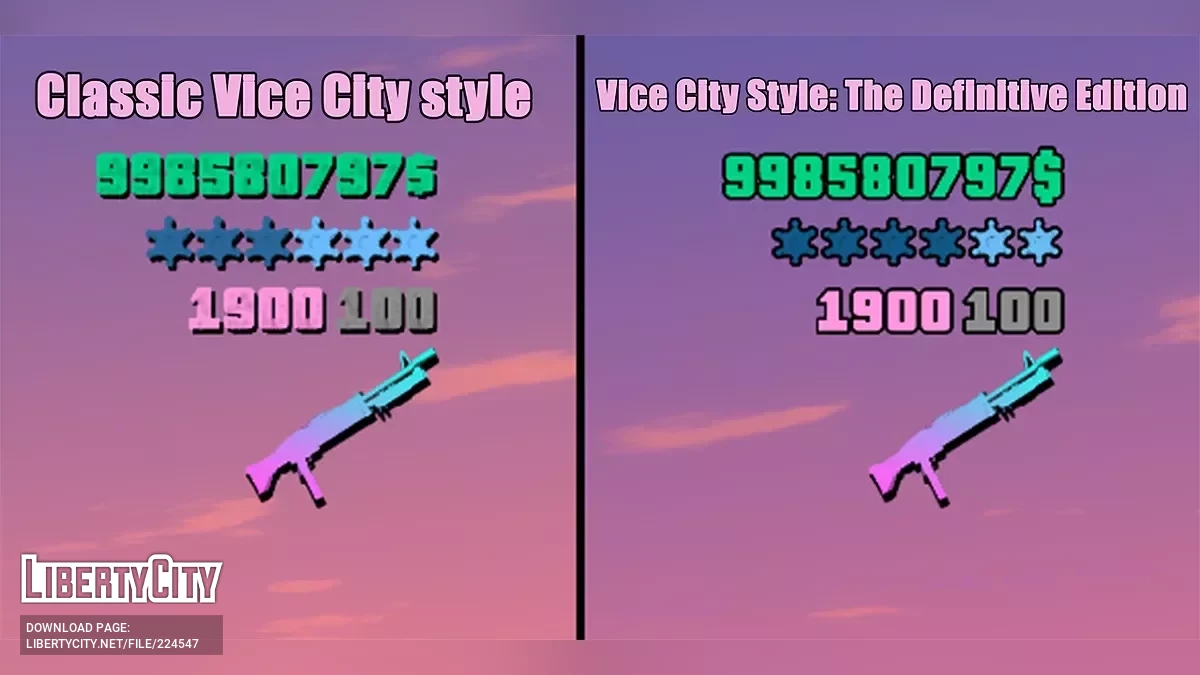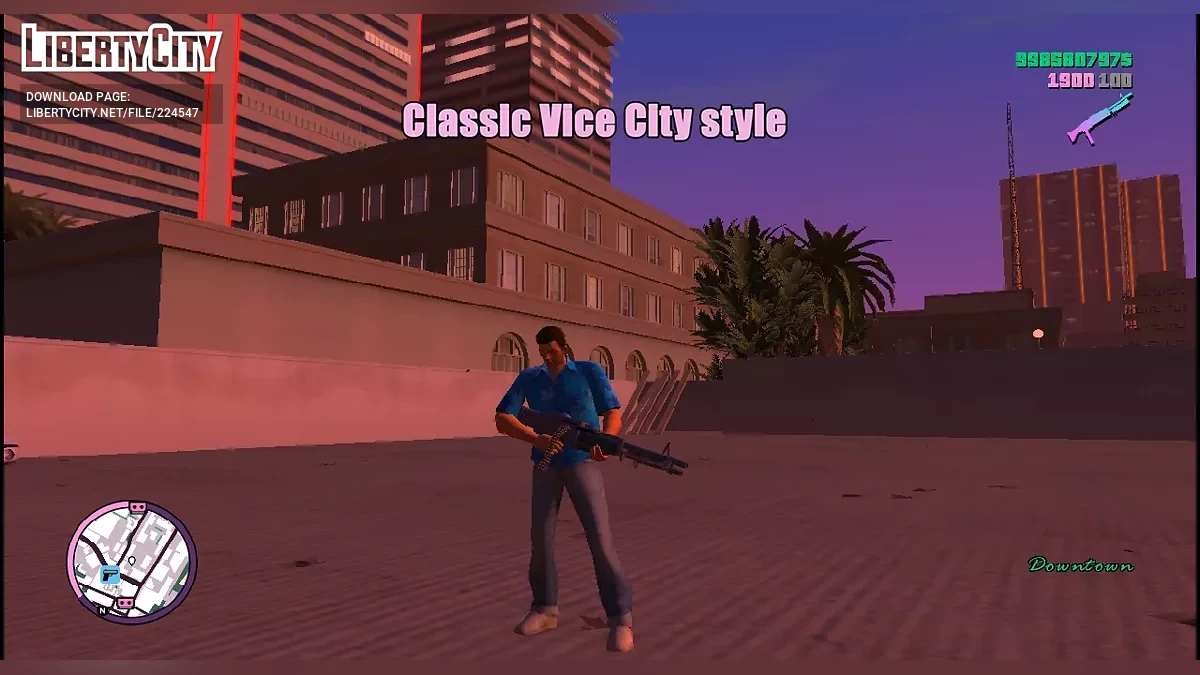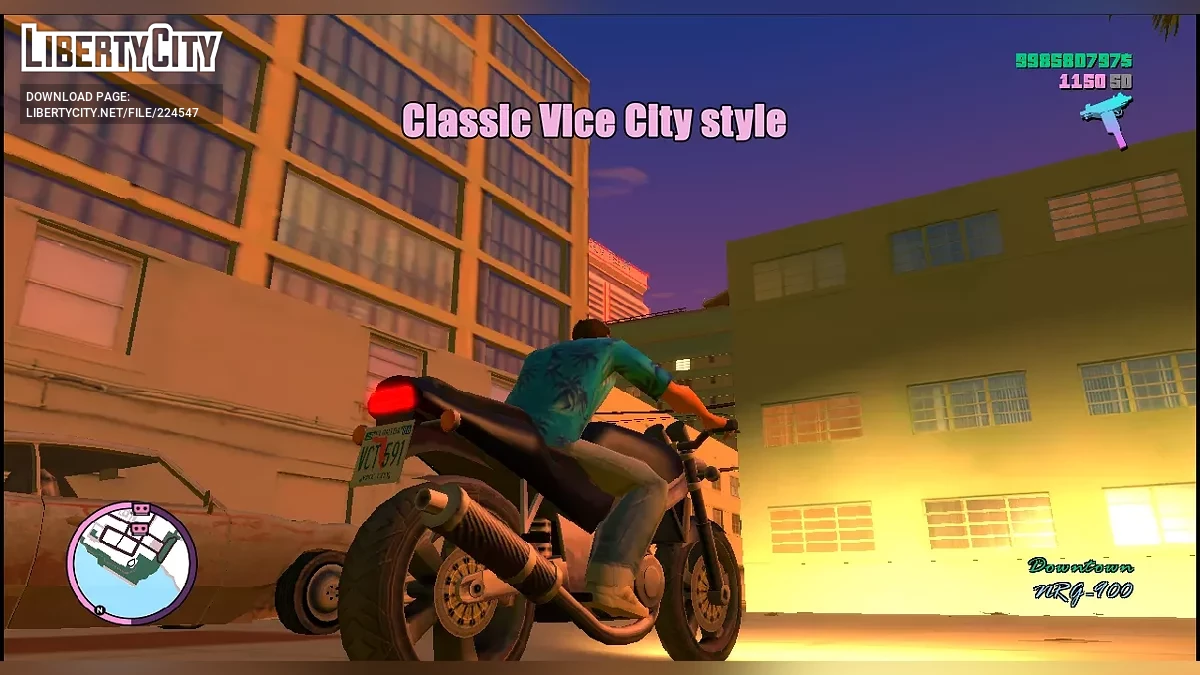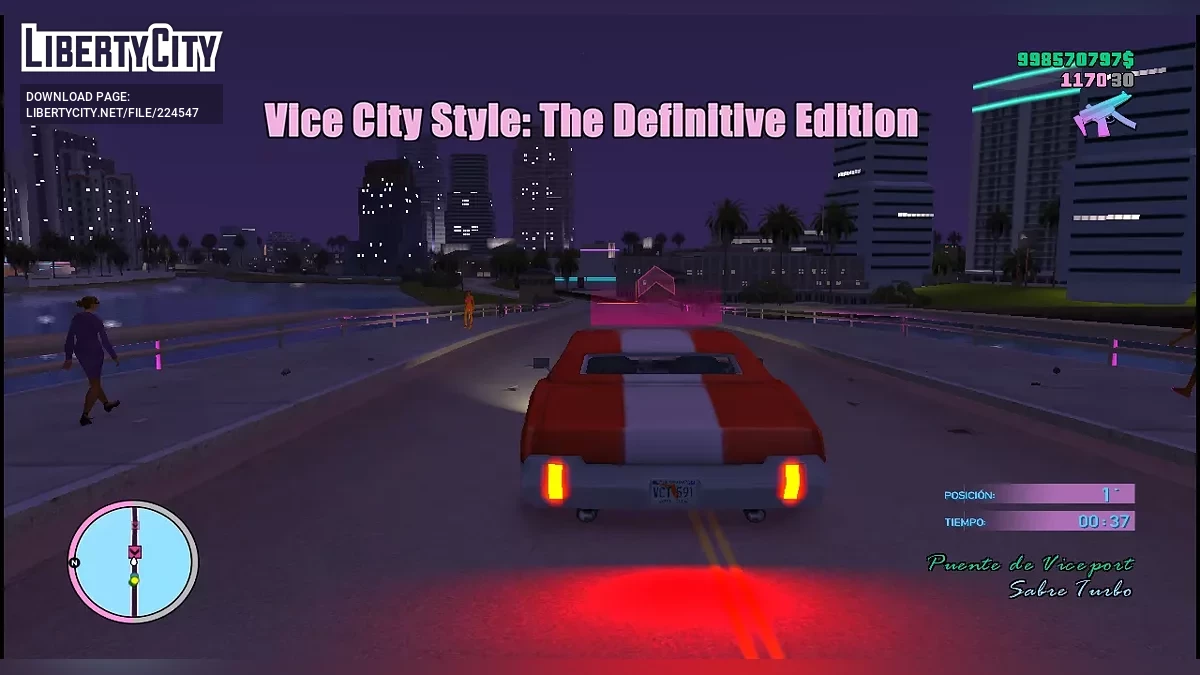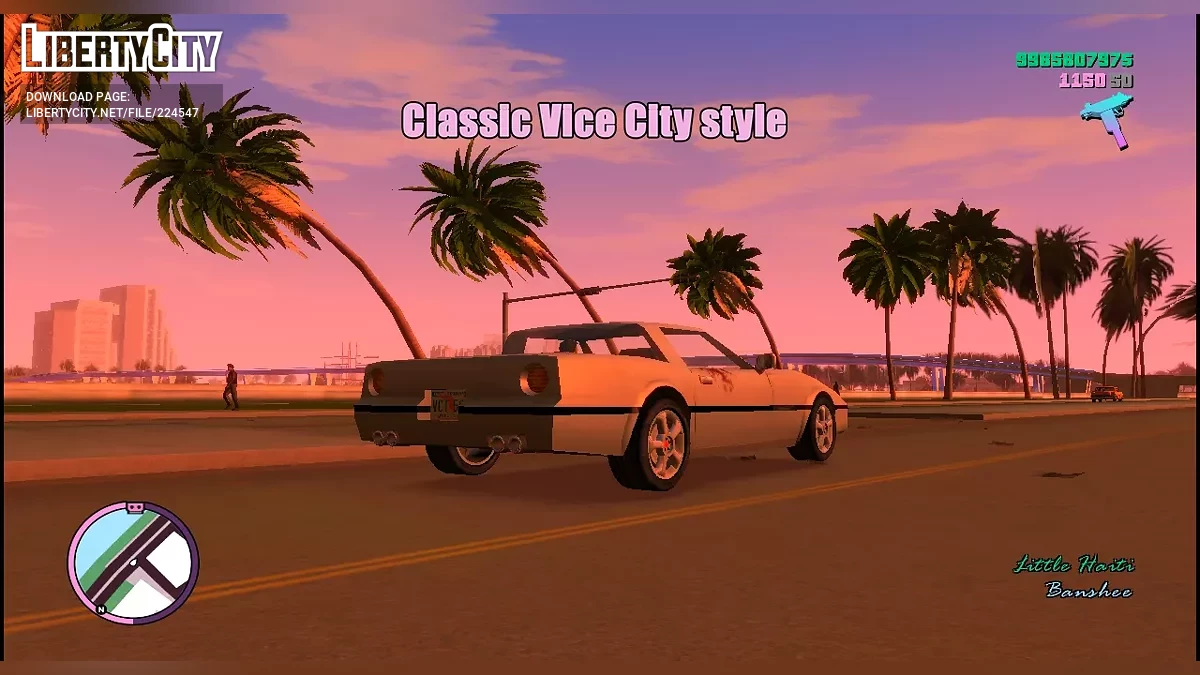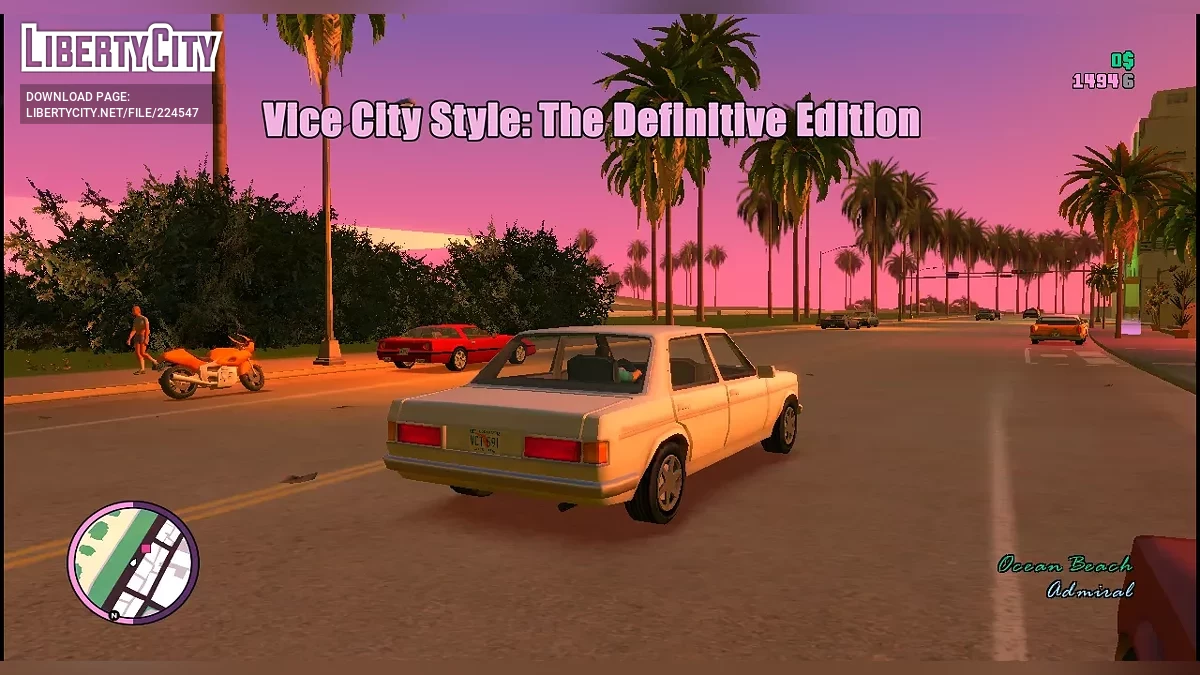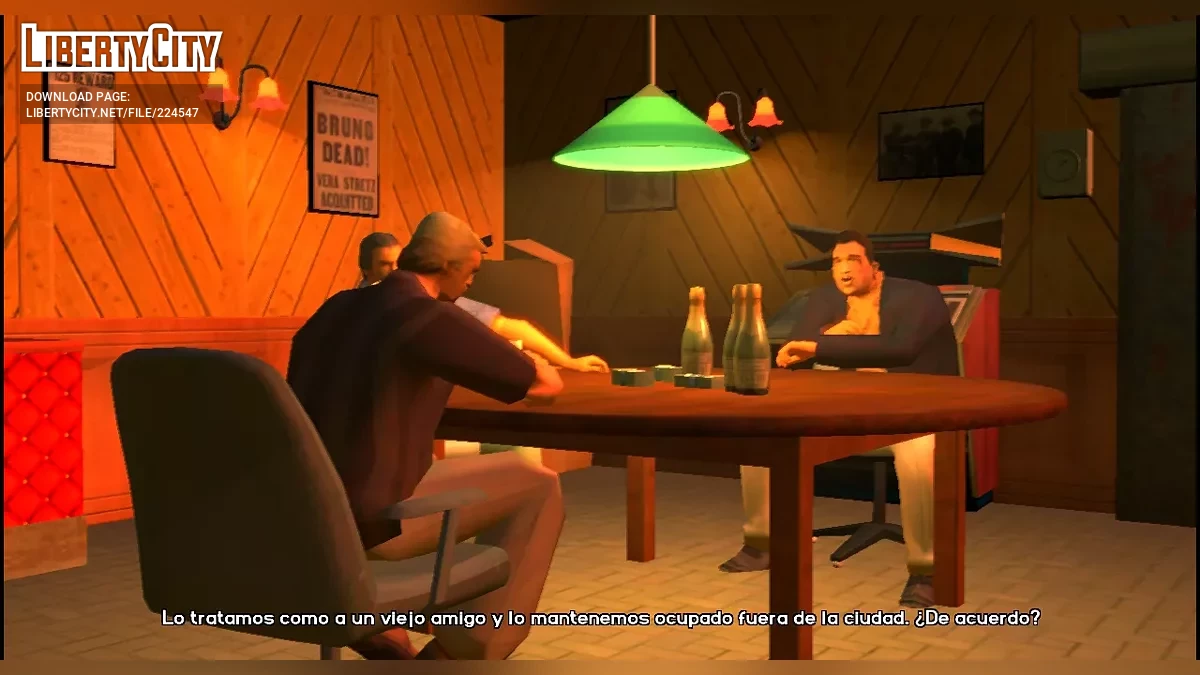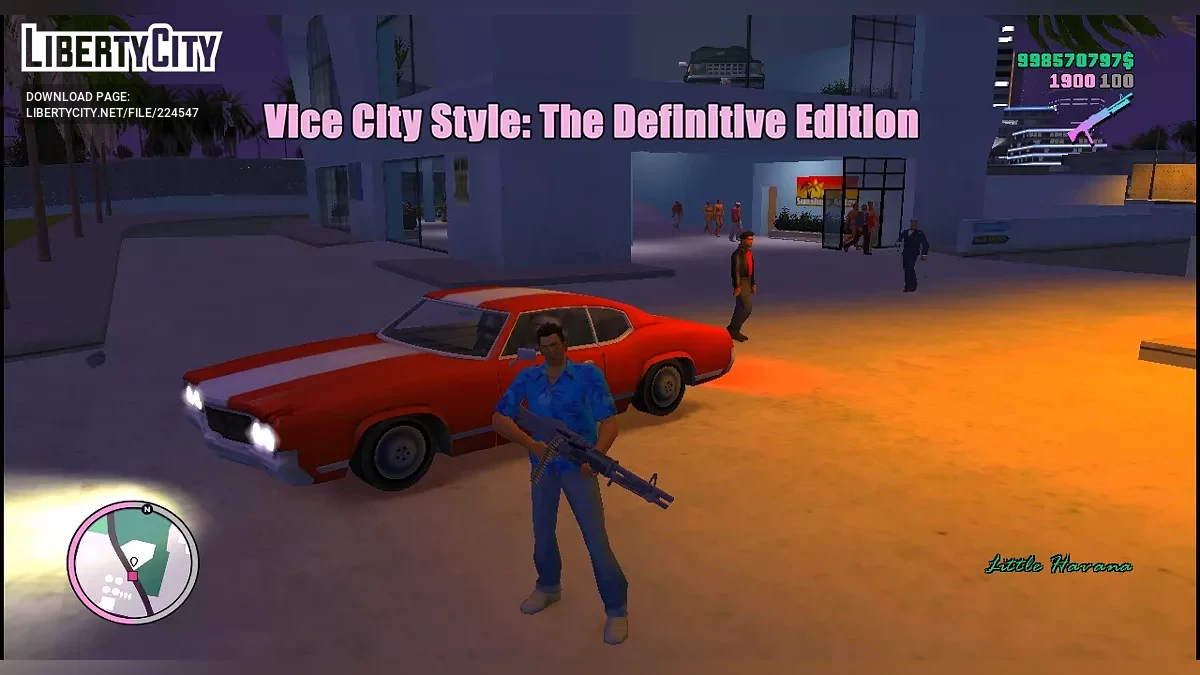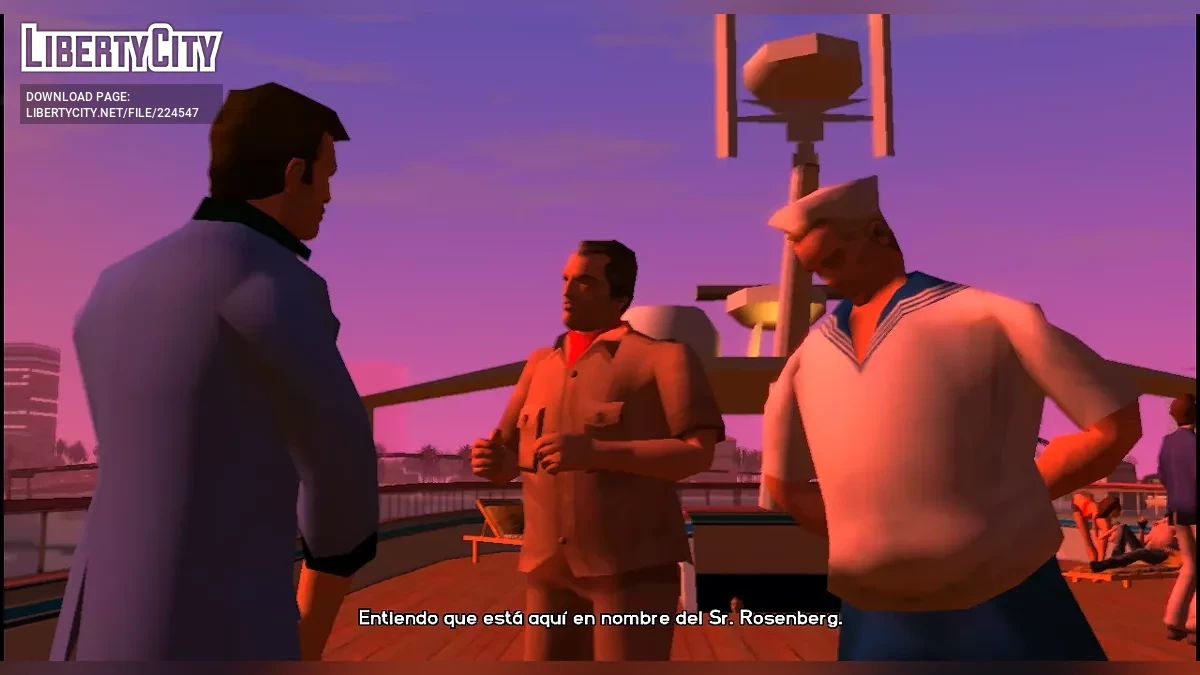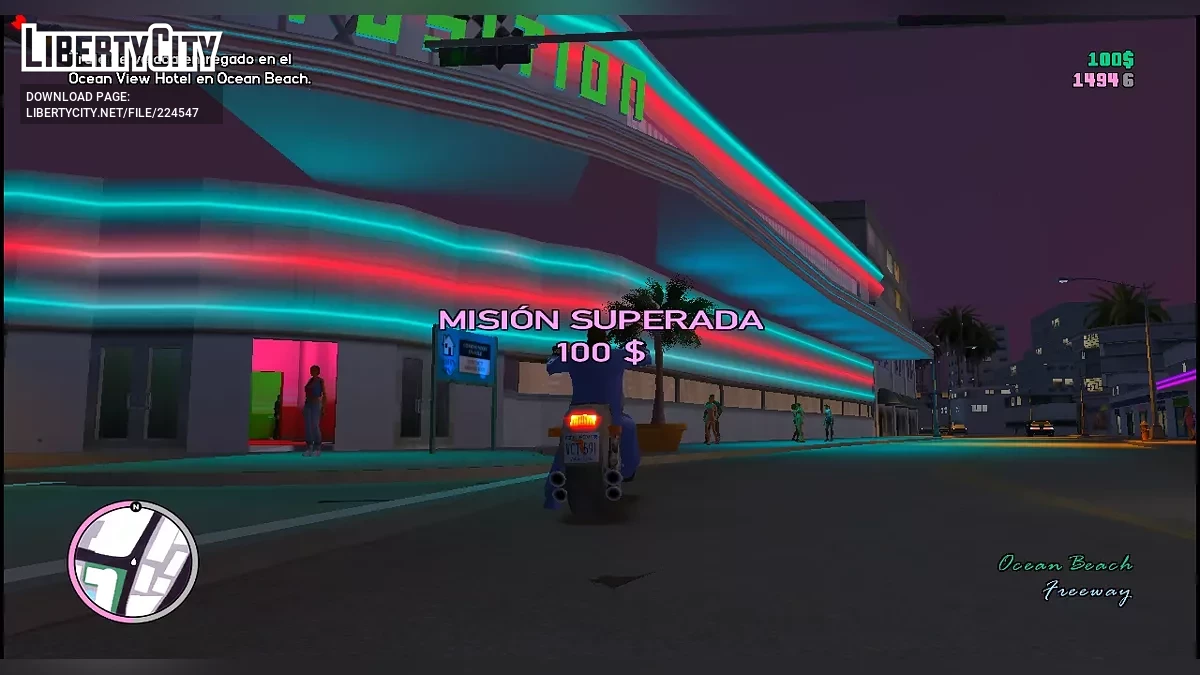
Новые шрифты, как в оригинальной Vice City v2
Вторая версия улучшенного шрифта, более точно передающего стиль оригинального GTA Vice City.
- Два стиля отображения денег и патронов:
- Classic Style — как в предыдущей версии мода;
- Definitive Edition Style — в стиле обновлённого Vice City.
- Шрифт субтитров из классической версии игры;
- Исправлены отступы между буквами, улучшена читаемость;
- Корректное отображение названий транспорта и локаций.